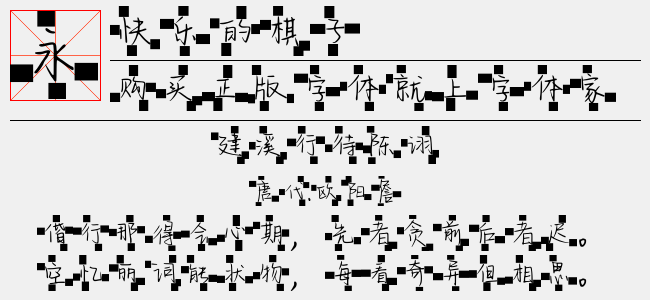
快乐的棋子
字体作者:红豆字库
字体名称:快乐的棋子
字体家族:红豆字库
书体类型:手写体、印刷体
快乐的棋子
快乐的棋子是一款非常不错的艺术字体,由红豆字库出品,个性醒目,具有强烈的视觉冲击力,适应于报纸和杂志和书籍中常用字体, 海报、个性促进品牌标志设计、字体设计、等环境使用,欢迎喜欢的朋友前来字体家下载使用。